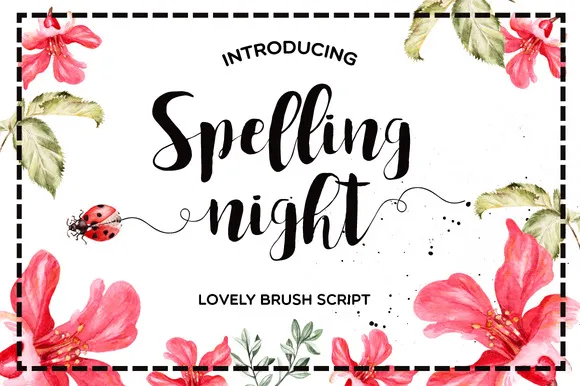
A fonte Spelling Night é perfeita para quem busca uma aparência elegante e sofisticada para qualquer projeto visual. Desenvolvida pelo designer Hamilton, essa fonte é ideal tanto para criar cartões de convite ou postais para amigos especiais quanto para criar logotipos memoráveis e posters bonitos. Além disso, sua versatilidade permite que você use a Spelling Night em pequenos negócios, oferecendo uma opção estilosa para qualquer projeto visual onde seja necessário o uso de fontes. Com seu design detalhado e elegante, a fonte Spelling Night é um excelente complemento para trabalhos de arte e design. Engajando-se com a elegância da Spelling Night não só tornará seus projetos mais profissionais, mas também assegurará que eles se destacam do resto da multidão.